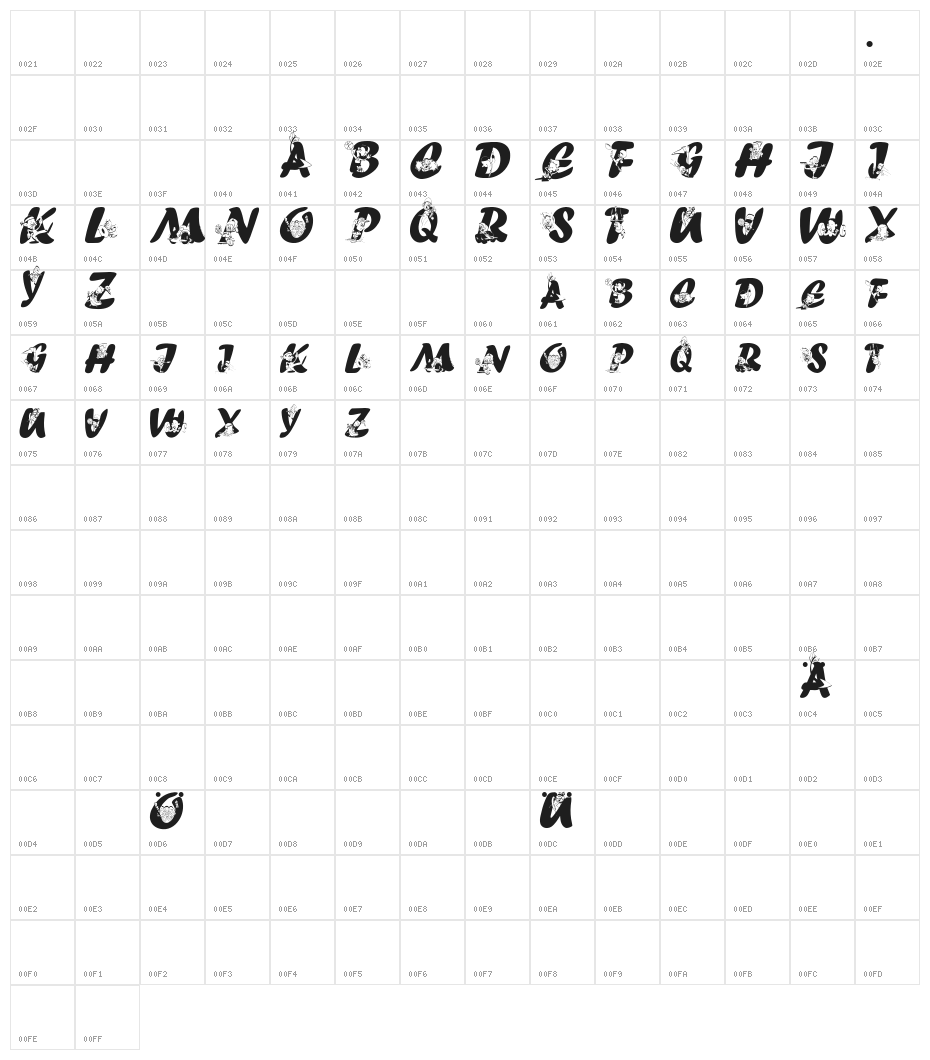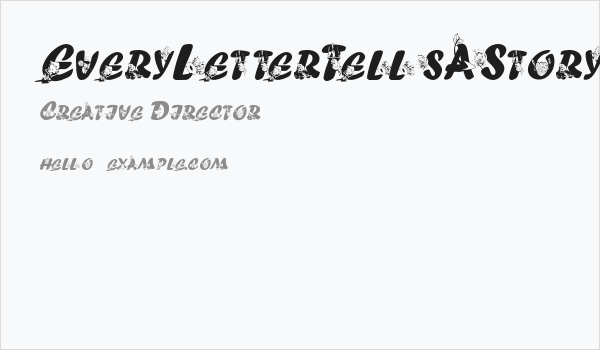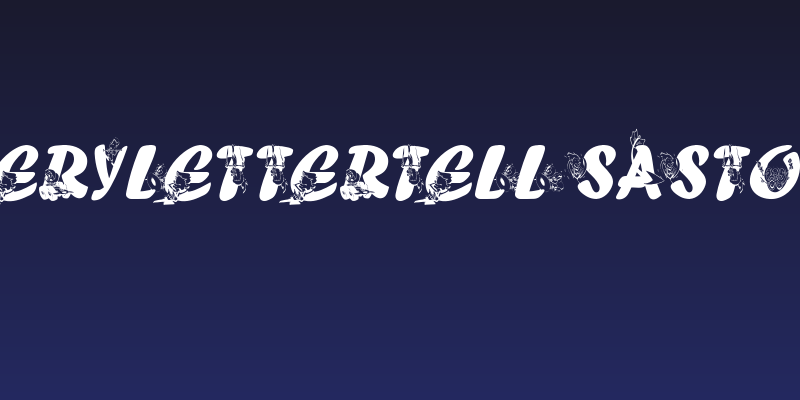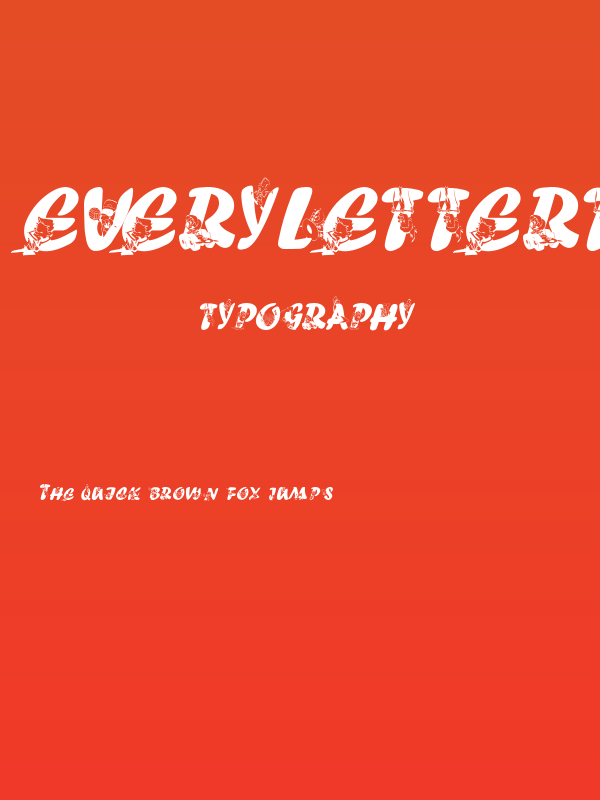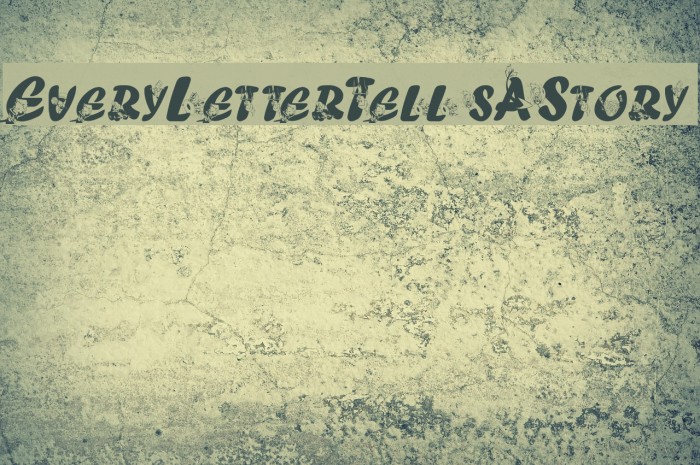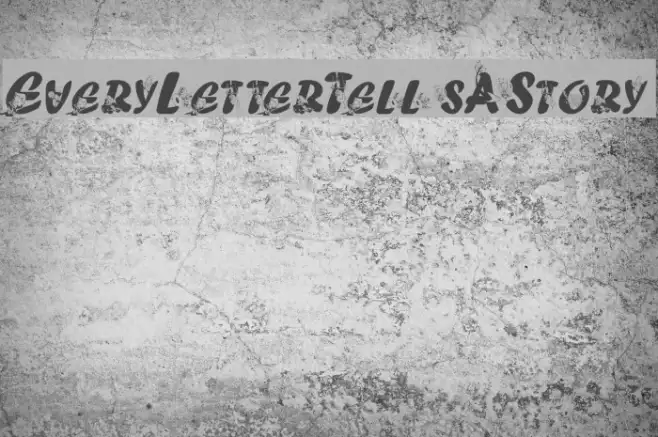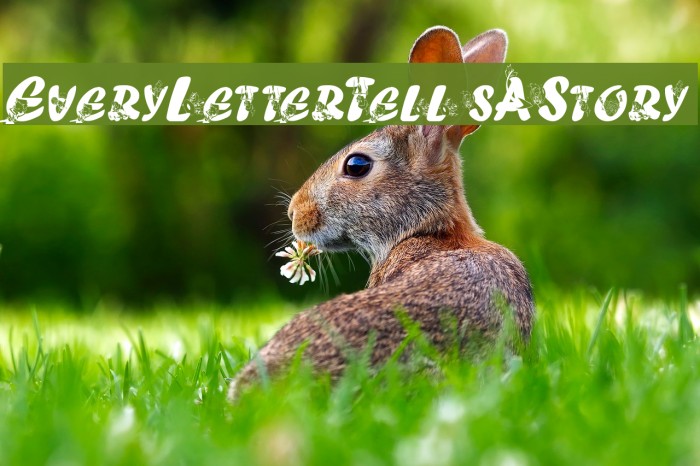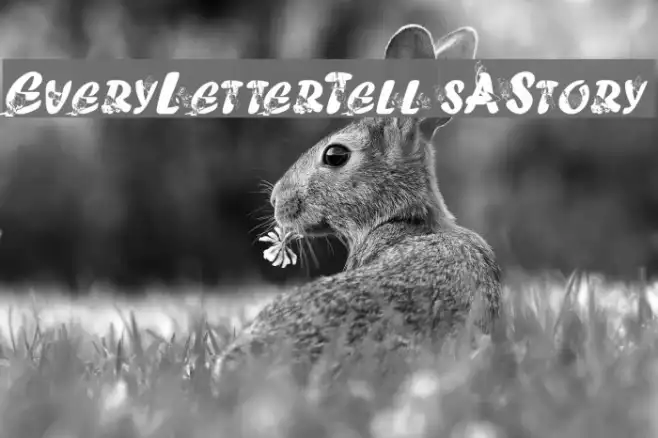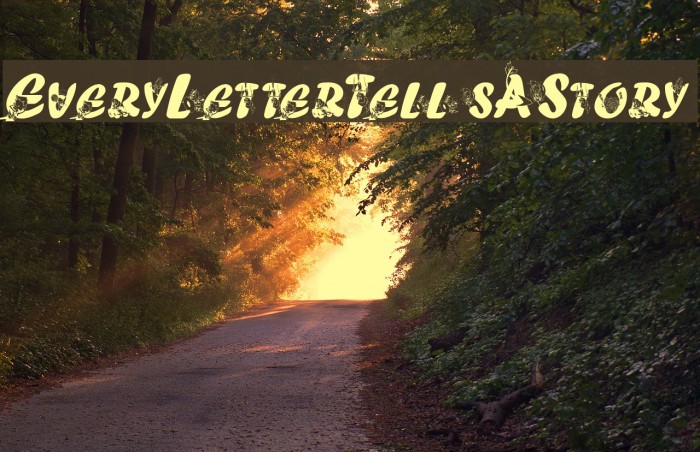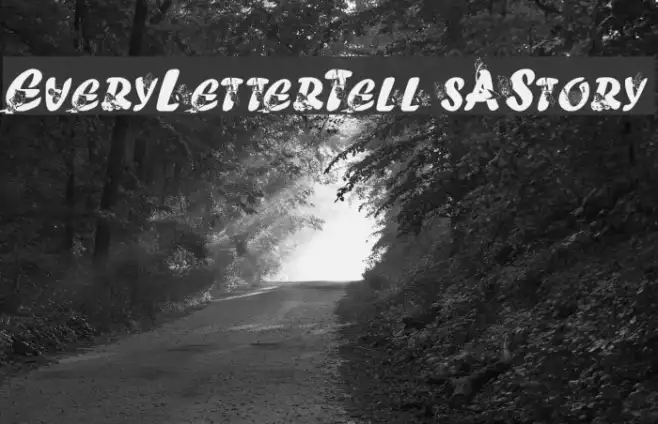
EveryLetterTellsAStory Font
| Caso d'uso | Logos, Headlines, Artistic Designs |
| Progetti proposti | Ideal for greeting cards, wedding invitations, artistic posters, and branding that requires a whimsical touch. |